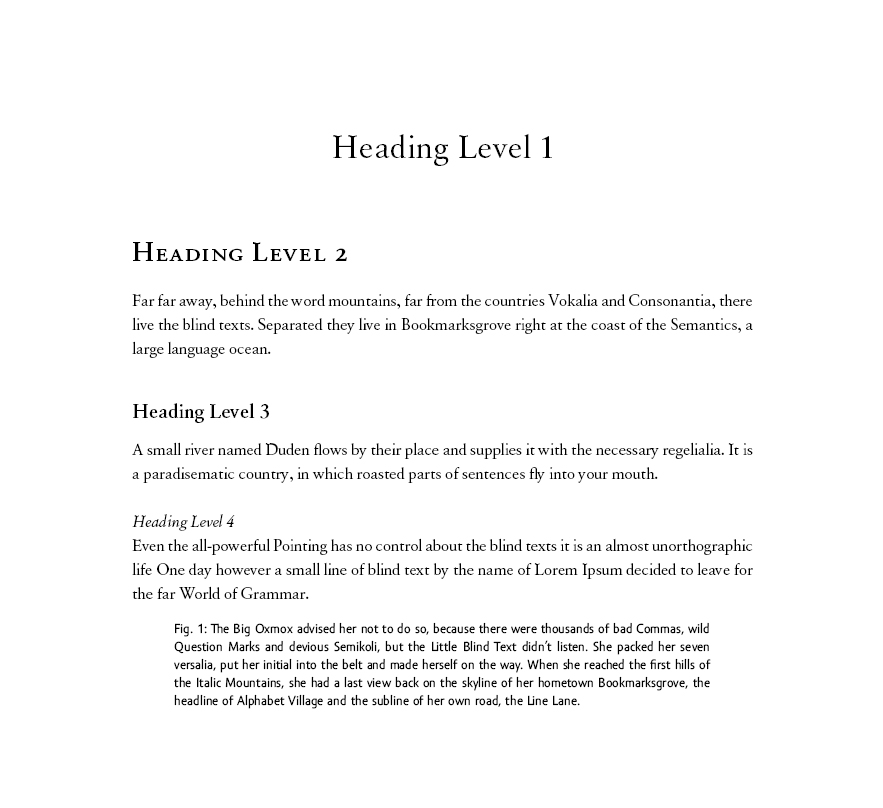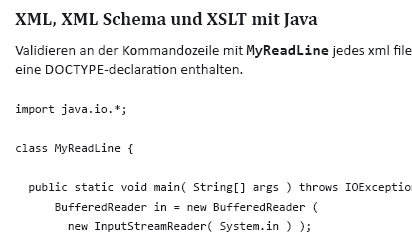
Diplomarbeit mit Fließtext, Bildbeschriftungen und Code
ich bin gerade in der Arbeit an einer Informatik-Diplomarbeit. "Obwohl" es Informatik ist, möchte ich die Arbeit nicht in Arial 11 erstellen, sondern sie auch typographisch ordentlich abliefern, zumal es nicht nur um Algorithmen, sondern auch um konkrete Anwendungsfälle geht.
Folgende Bereiche möchte ich typographisch auszeichnen:
• - Fließtext
- Überschriften
- Bildbeschriftungen (d.h. Bildunterschriften und Texte innerhalb des Bilds)
- Programmcode (in geringem Anteil, d.h. immer nur einzelne Zeilen)
Ich dachte dabei an folgende Kategorien:
• - Antiqua für den Fließtext
- Grotesk für Überschriften und Bildbeschriftungen
- Dicktengleiche Grotesk für Codebeispiele
Und jetzt wird es kompliziert, denn ich möchte die Arbeit nicht typographisch überfrachten! Welche Familien kombiniere ich hier am besten? Spontan hätte ich an die Bembo als Brotschrift gedacht, aber welche dazu passende Grotesk gibt es sowohl dicktengleich als auch proportional? Nur die "Spezialsippen" wie z.B. Thesis?
Ihr seht, dass mein Problem der Programmcode ist. Die immer mal wieder vorkommenden einzelnen Codezeilen sollen durchaus anders ausgezeichnet ein, aber sie sollen nicht das gesamte Erscheinungsbild der Seiten aufbrechen.
Ohne den Code könnte ich eine klassische Kombination wie z.B. Garamond-Frutiger nehmen. Aber dann immer mal wieder Codezeilen dann noch in Letter Gothic oder Courier, das sieht einfach nicht aus - finde ich zumindest.
Somit willst Du die Arbeit schreiben? Meiner Meinung nach spricht für eine Informatik-Arbeit nichts gegen (La)TeX mit seinen Standardfonts, bzw. den verbesserten lmodern-Varianten. Da müsstest Du Dir auch keine Sorgen machen, ob die einzelnen Schriften zusammenpassen.
Alles Windows Vista Systemfonts
Consolas (ausgezeichnete Codeschrift!)
Sans: Calibri
Serif: Cambria
Für die genannten Schriften gibt es die Schriftschnitte Regular, Italic, Bold, Bold Italic.
Ich würde die Calibri für den Fliesstext nehmen. Und für Code innerhalb des Fliesstextes die Consolas 2pt kleiner eingestellt und in Bold. Oder Regular bzw. Bold mit Farbauszeichnung versehen. Auf die Cambria bzw. eine andere Serif könnte man verzichten oder halt als Headlinefont verwenden.
Hier also doch die Cambria als Headliner. Calibri und Consolas im Fliesstext. Und als Code die Consolas. BTW Text ist natürlich Schwachsinn …
an die "neuen" Standardfonts hatte ich gar nicht gedacht und sie mir auch nicht näher angesehen. Von daher danke für den Tip und für das anschauliche Beispiel! Die Consolas sieht wirklich sehr gut aus, ist sie denn auch für den Ausdruck geeignet oder "nur" für den Bildschirm, sprich: für ClearType optimiert? Ich bin gespannt...
Serifenlos für Fließext und Serifen für Überschriften ist natürlich auch eine Möglichkeit, aber ich finde das optisch nicht so attraktiv. Vielleicht bin ich altmodisch, aber für mich muss ein Fließtext Serifen haben... nichtsdestotrot sind die beiden Vista-Schriften sehr schön, insbesondere die Calibri gefällt mir sehr gut (kein Wunder, sie stammt wie die Thesis von Luc de Groot...)
Somit willst Du die Arbeit schreiben? Meiner Meinung nach spricht für eine Informatik-Arbeit nichts gegen (La)TeX mit seinen Standardfonts, bzw. den verbesserten lmodern-Varianten. Da müsstest Du Dir auch keine Sorgen machen, ob die einzelnen Schriften zusammenpassen.
Es ist zwar eine Arbeit im Fach Informatik, aber Schwerpunkt werden wirtschaftliche Anwendungen mit viel Diagrammen, einigen Code-Schnipseln und wenigen Formeln werden. Der Schwerpunkt liegt also schon auf dem Text. Und da ich es die letzten Jahre geschafft habe, ohne (La)TeX auszukommen, wollte ich mich nicht erst kurz vor dem Diplom einarbeiten... von daher: Word oder PageMaker, äh, InDesign.
Und da ich es die letzten Jahre geschafft habe, ohne (La)TeX auszukommen, wollte ich mich nicht erst kurz vor dem Diplom einarbeiten...
Na komm, wenn so ein simpler Bücherwurm und Germanist wie ich es schafft sich die Befehle zu merken und die Klammern nicht zu sehr in Unordnung zu setzen, dann wird ein Informatiker kurz vorm Abschluss das doch wohl auch schaffen!
PS: Meine persönlichen Ansichten zu Typo und TeX habe ich endlich mal typografisch webtauglich gemacht, so dass ich darauf wieder guten Gewissens verweisen kann.
Arbeite dich in Indesign ein, hehe.
Ok, Fliesstext ist für dich eine Serif … die Charis SIL ist eine Variation der ITC Charter, kostet nichts und sieht dafür sehr gut aus und hat zudem als Unicode-Schriftart extrem viele Glyphen und 4 (!) Schriftschnitte.
>Die Consolas sieht wirklich sehr gut aus, ist sie denn auch für den Ausdruck geeignet oder "nur" für den Bildschirm
Ich finde die meisten Codeschriften sind viel zu bleich im Ausdruck, vorallem im Vergleich zu den Textschriften. Auch – hierbei ist die Consolas ein Qualitätsprodukt von Luc de Groot (und Ascender) mit dem positiven Nebeneffekt, dass sie via Cleartype auch hübsch am Monitor aussieht … also sich sehr gut zum Arbeiten im Editor eignet und zusätzlich in einem Screen-PDF eine gute Figur macht.
Bei technischen Arbeiten sind vier Ebenen eigentlich ganz in Ordnung, die erste Ebene ist, gerade bei einer Dissertation, an der man drei Jahre oder länger gewerkelt hat, so allgemein, daß man meist um eine weitere Differenzierung nicht drum herum kommt, ...
Das ist mir auch klar, aber die Frage nach Dissertation stellt sich bei mir nicht. :?
Na, dann mußt Du eben mit 3 Ebenen auskommen! :twisted: